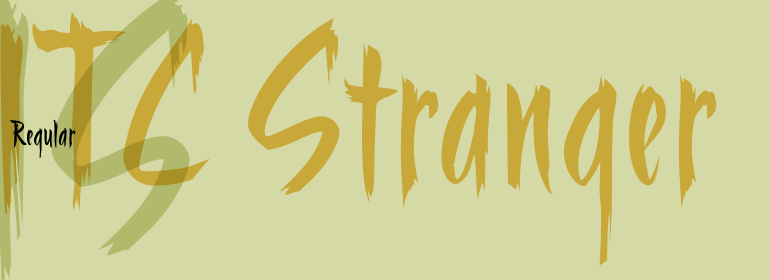
ITC Stranger™
ITC Stranger™,这款字体结构工整、笔画清晰,兼顾美观与易读性,适用于标题、正文、海报、包装、LOGO 等多种场景。字形优雅稳定,风格百搭耐看,适配日常排版与创意设计,让文字呈现更舒适、更具质感。ITC Stranger™一笔一画,皆是细节,以均衡的比例、流畅的线条打造舒适视觉体验,字形端正大气,风格简约现代。无论是商业设计、品牌宣传还是日常排版,都能轻松驾驭,让文字更有格调与力量。ITC Stranger™字体下载。
The slashing, almost menacing style of ITC Stranger comes from quick calligraphic strokes done with a partly dry brush - or the digital illusion of the same - in a very narrow, upright style. The effect in small sizes is spiky, because what you see is mos